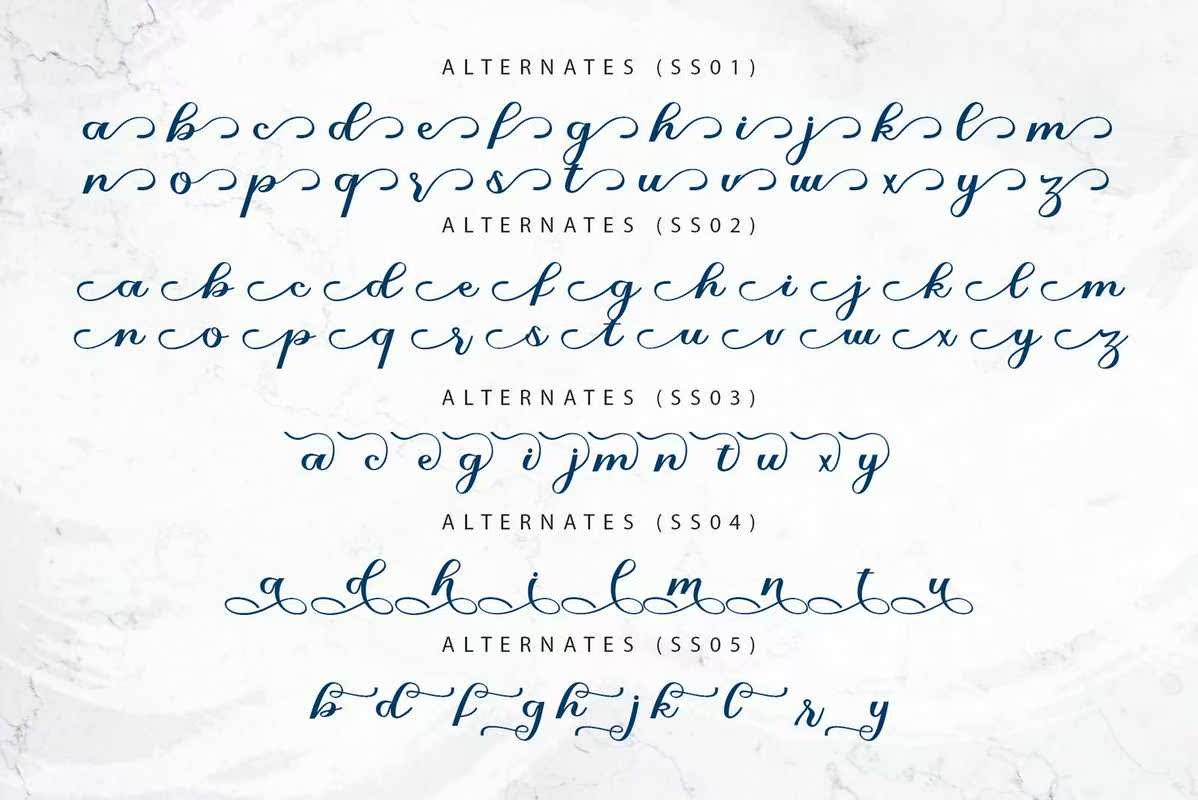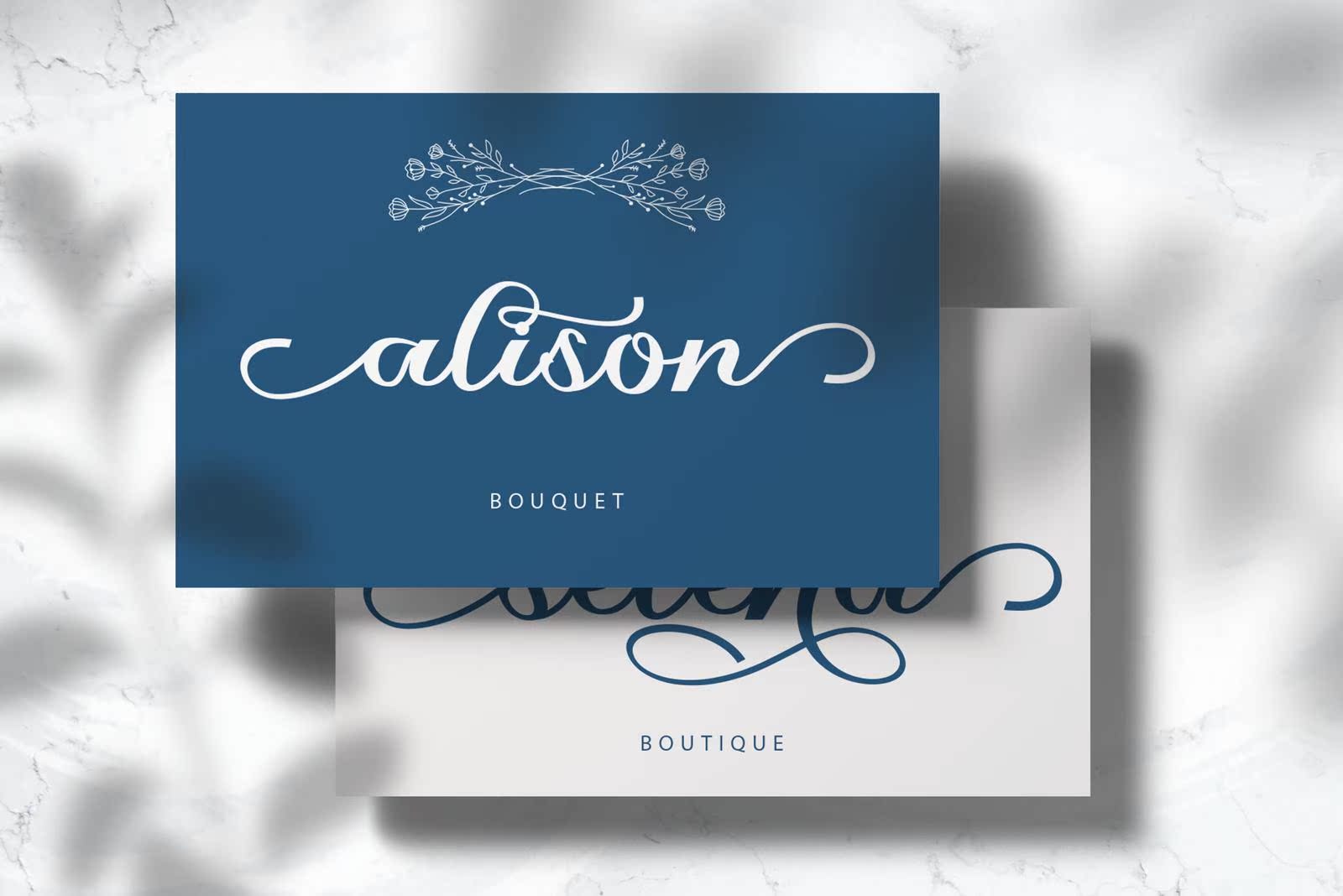
Athabasca Modern and Write字体。适合您的项目的文字和数字集合非常适合于标识、品牌设计、标识设计、数字刻字艺术、T恤/服装、海报、杂志、标志、广告设计和任何设计需求。Athabasca Modern and Write字体。适合您的项目的文字和数字集合非常适合于标识、品牌设计,标志设计、数字文字艺术、T恤/服装、海报、杂志、标志、广告设计和任何设计需求。